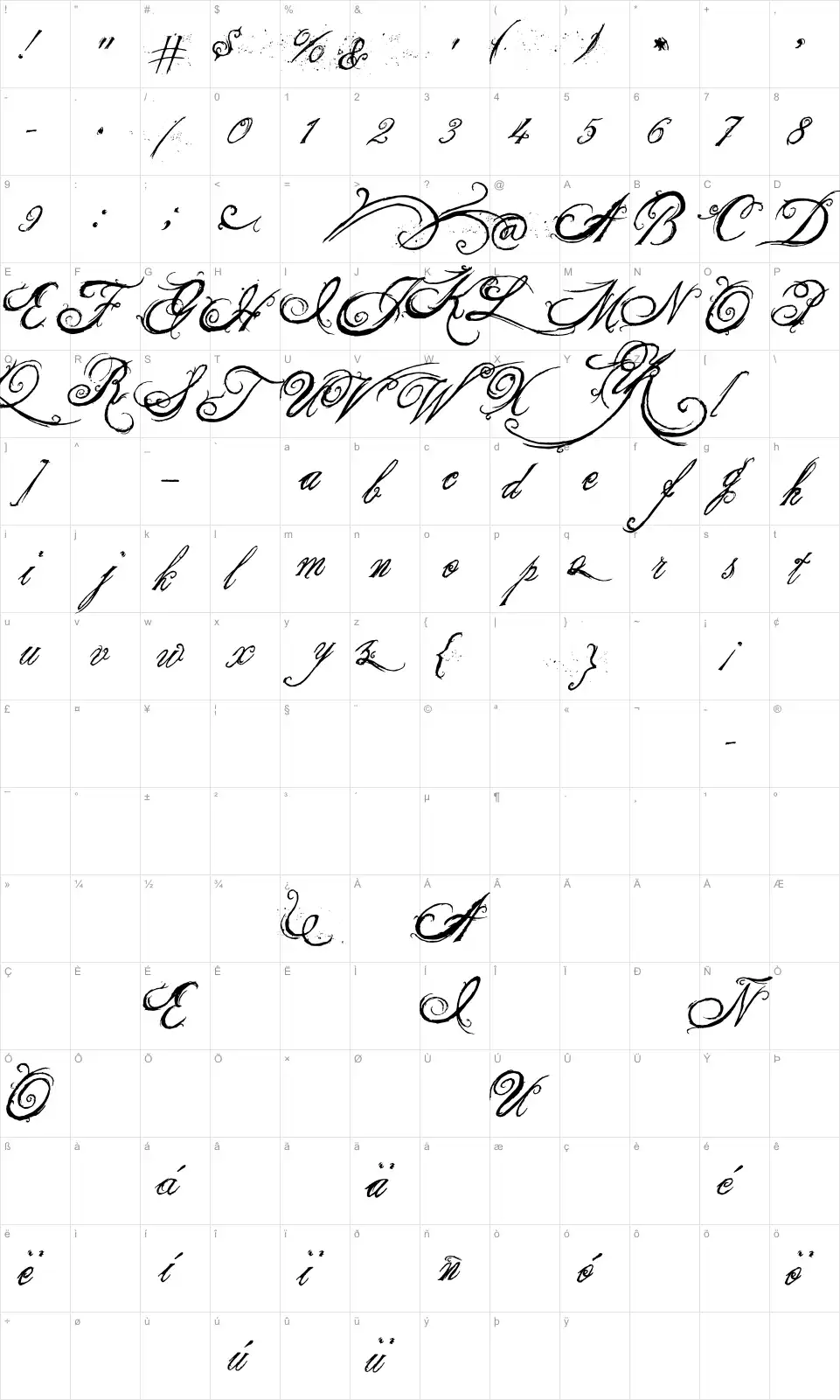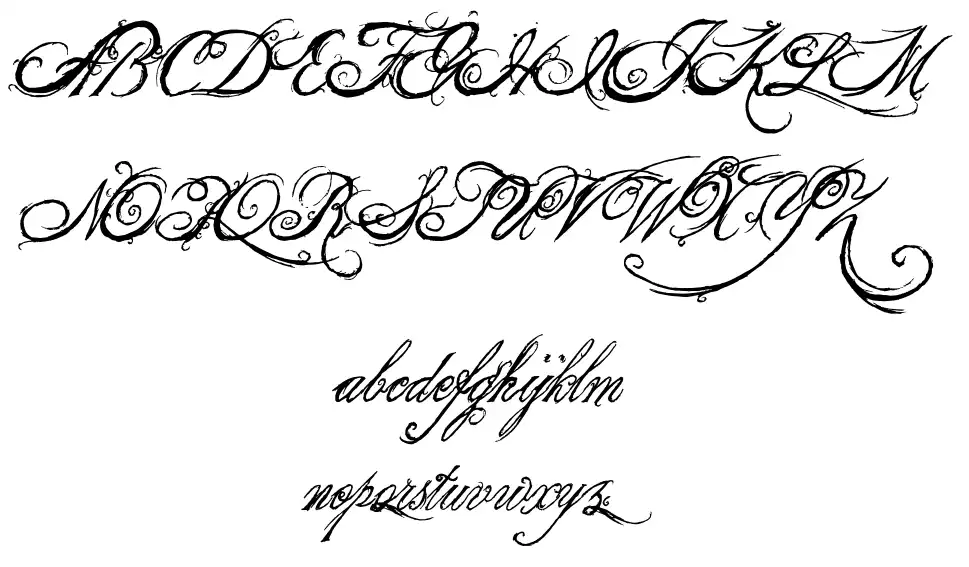
The King & Queen font – Fonte Grátis
The King & Queen font
A fonte The King & Queen, criada pelo designer bran, é uma opção interessante para quem está buscando uma fonte de script para textos legíveis e elegantes. Com apenas 142 KB, ela é bastante compacta para ser facilmente baixada e instalada. A fonte está disponível sob uma licença gratuita, o que a torna acessível a todos. Adicionada em 12 de julho de 2022, The King & Queen já teve grande aceitação entre os usuários que buscam uma fonte de script clássico e elegante. Com mais de 331.615 downloads até o momento, é evidente que muitos usuários encontraram no The King & Queen algo especial, tanto para projetos pessoais quanto para trabalhos profissionais. Esta fonte pertence à categoria Calligraphy, ou escrita, devido ao seu estilo elegante e à sua capacidade de criar letras e frases de formas fluidas e artísticas. Ideal para aplicações como cartazes, editoriais de revistas, e até mesmo para criar textos em artesanato, The King & Queen oferece um toque de sofisticação a qualquer design que ela encoraja. Para ter uma visão prévia de como a fonte ficará em seu próximo projeto, você pode facilmente baixá-la ou gerar um preview personalizado online.
Categoria: Script › Calligraphy